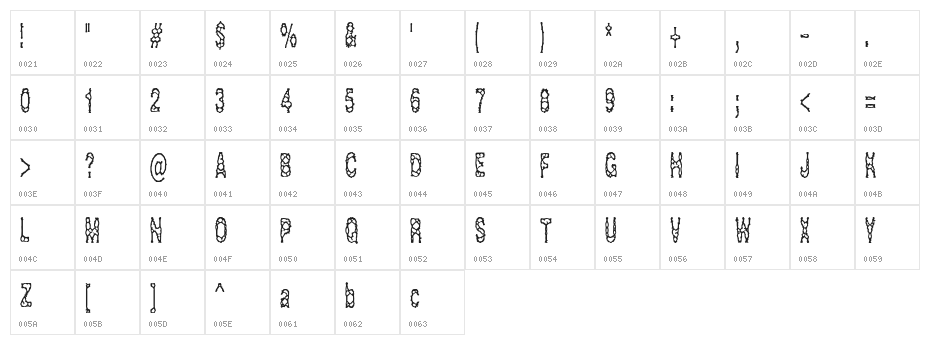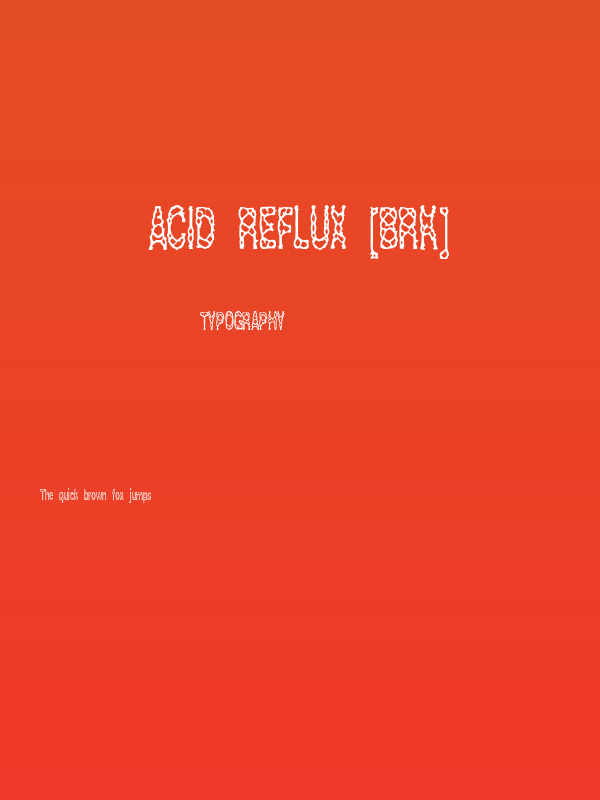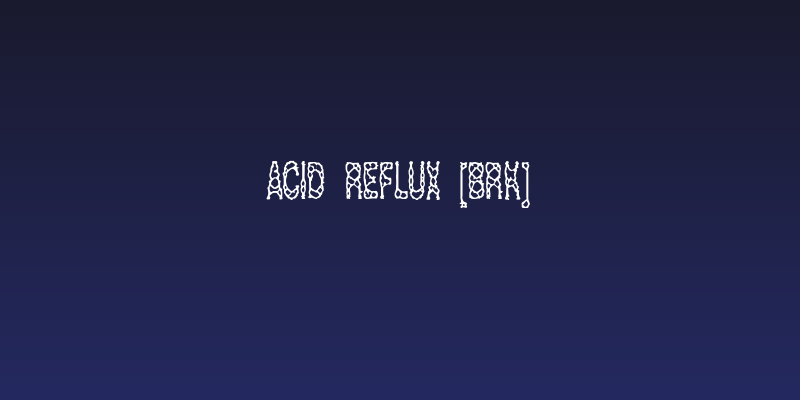
Acid Reflux [BRK] Font
| Progetti proposti | Ideal for horror-themed posters, album covers, Halloween invitations, or any project needing a dramatic and edgy typeface. |